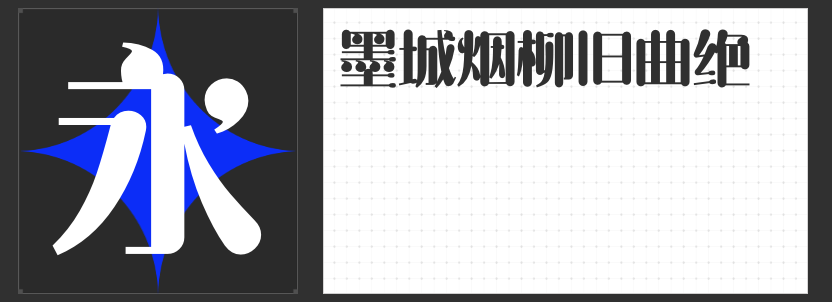
影视设计专属字体推荐:四款创意字库的视觉魔法
在影视设计的视觉叙事中,字体是传递情绪、强化风格的关键元素。今天推荐四款极具表现力的付费字体,它们以独特的形态语言,为影视作品注入灵魂。
一、字恋狂嗨玩简
这款字体以粗壮的方块笔画构建出积木般的童趣感,重心下沉的设计赋予文字憨态可掬的视觉张力。其笔画转折处保留了孩童涂鸦的稚拙感,却通过精密的几何结构保持整体平衡,适合用于儿童题材影视的片头字幕或动画场景。例如在奇幻冒险类作品中,用其呈现角色昵称或魔法咒语,能瞬间唤醒观众的童真记忆。
二、励字明姿简
以几何图形为骨骼的创意美术字,竖笔如魔法杖般挺拔,横笔则以纤细线条勾勒出轻盈感。其笔画转折处采用圆角处理,既弱化了尖锐感,又保留了动态张力。在青春校园题材影视中,可作为片名或章节标题的视觉符号,例如在讲述少年成长的故事里,用其呈现“梦想”“勇气”等关键词,能精准传递热血与希望的主题。
三、小豆岛默陌写意水墨简
这款字体将传统书法与现代手写完美融合,笔尾锋芒如墨滴飞溅,连笔处又带着电子涂鸦的灵动。其灰度均匀的线条设计,使文字在动态影像中依然保持清晰辨识度。在古装武侠或文艺题材影视中,可作为卷轴字幕或诗词吟诵的视觉载体,例如在表现江湖恩怨的场景中,用其呈现“快意恩仇”四字,能瞬间营造出刀光剑影的意境。
四、字恋狂特别黑简
不规整的手写笔触与粗细对比强烈的横竖笔画,构成极具张力的视觉语言。其笔画边缘保留了毛笔飞白的质感,却通过数字化处理强化了现代感。在悬疑惊悚或反乌托邦题材影视中,可作为关键线索或危险提示的视觉符号,例如在犯罪题材作品中,用其呈现“真相”“罪证”等词,能瞬间强化紧张氛围。
这四款字体以截然不同的形态语言,为影视设计提供了丰富的视觉解决方案。从童趣积木到魔法几何,从水墨丹青到叛逆笔触,它们不仅是文字的载体,更是情感的放大器。在影视创作的视觉叙事中,选择合适的字体,往往能让故事在画面之外,多一层。